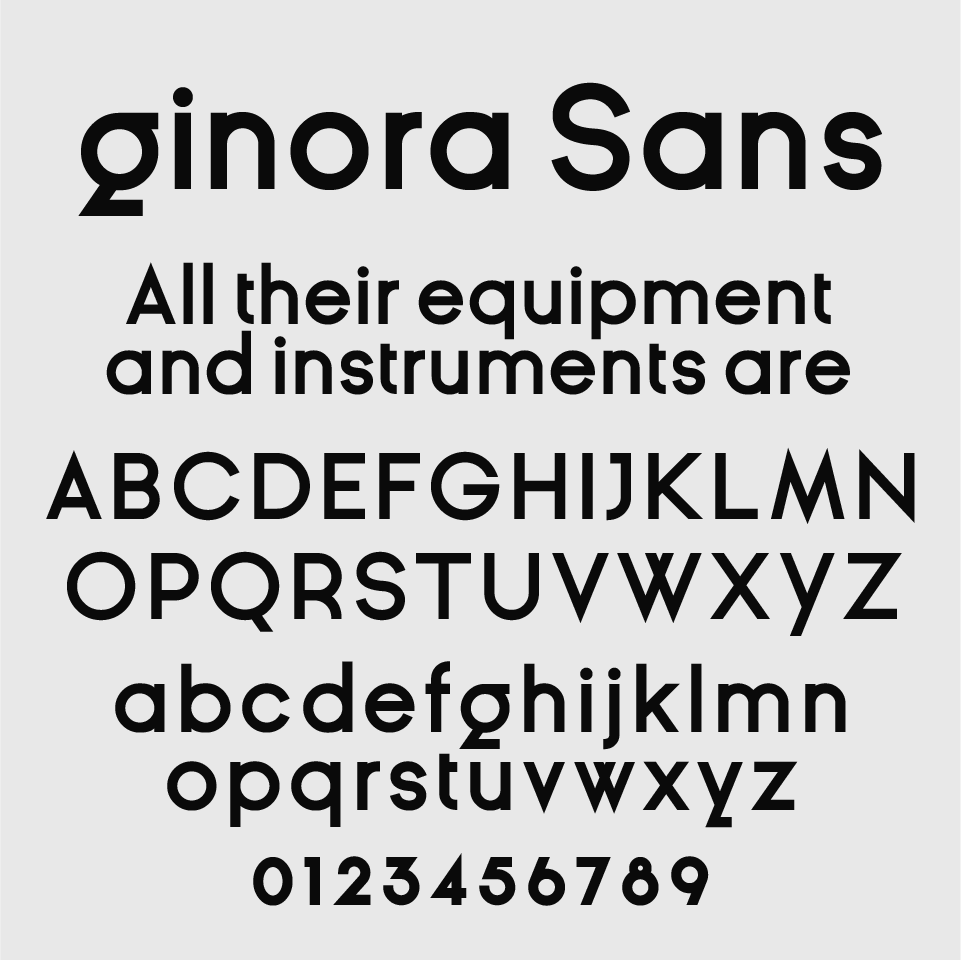
Ginora Sansフォントは、モダンで洗練された印象のサンセリフフォントです。
幾何学的でミニマルな構造ながら、丸みを帯びたカウンターがやわらかさを添えています。視認性とデザイン性のバランスが絶妙で、特に小文字の「g」がなどユニークのある字形が目を引きます。
ハイブランドやコスメ、洗練されたポスターやパッケージなど、クリーンで都会的な世界観にぴったりのフォントです。